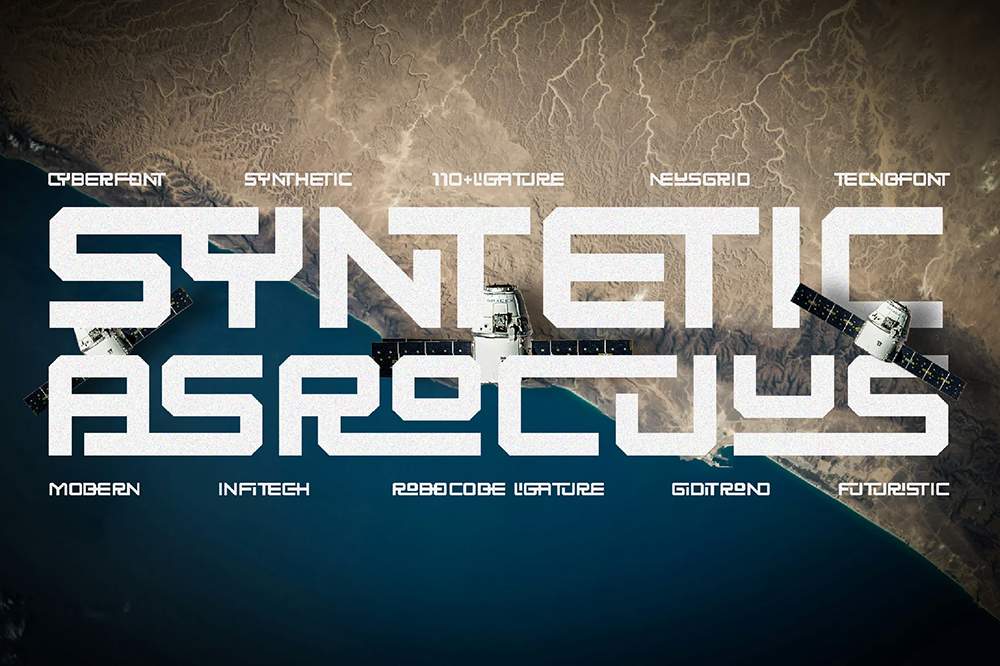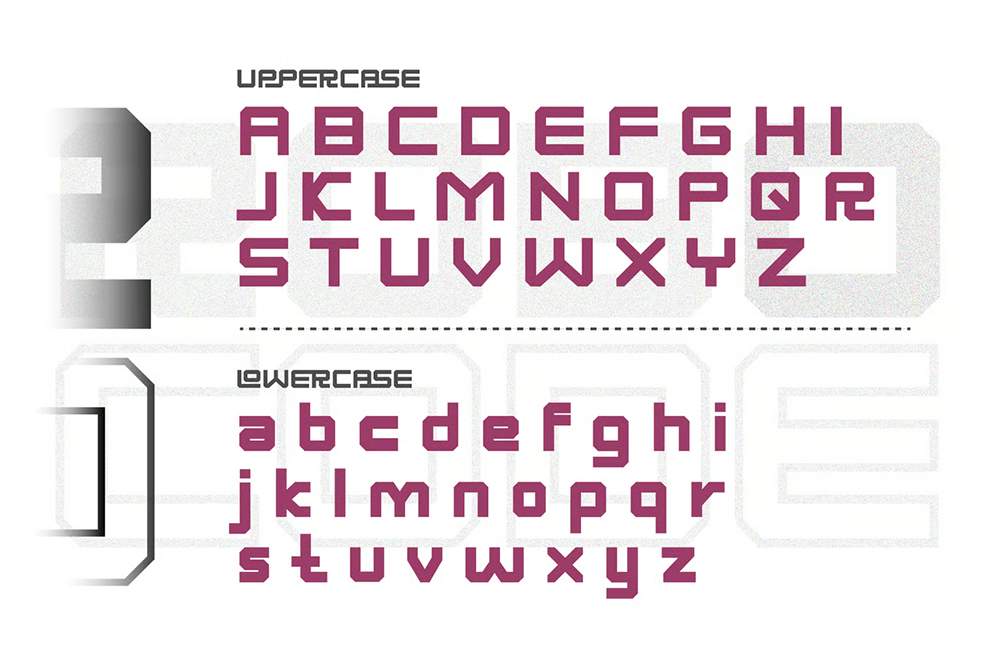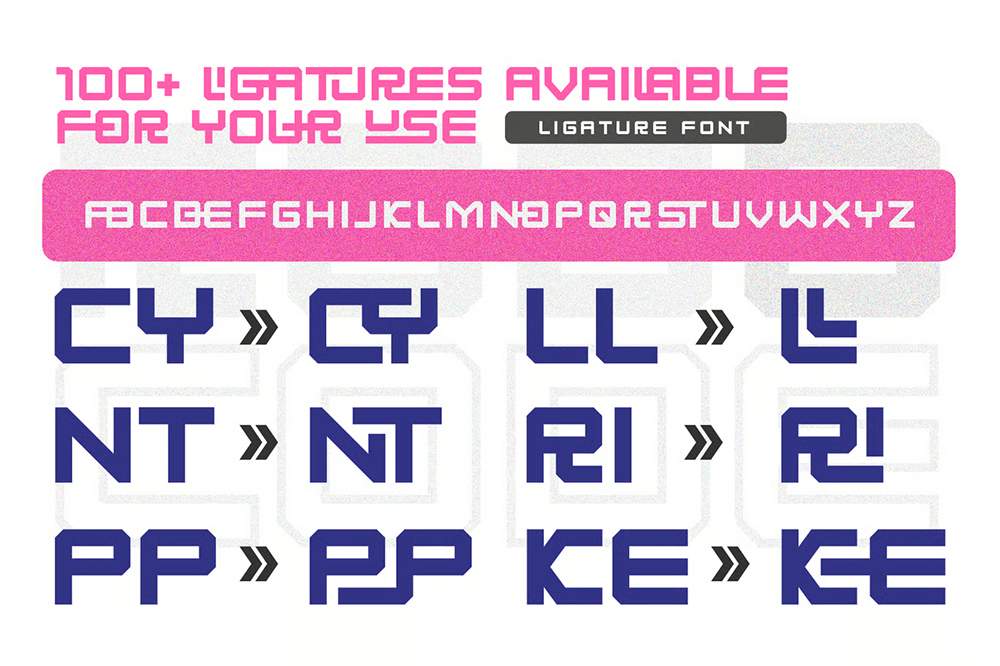
دانلود فونت انگلیسی Syntetic Asrocuus Font
فونت پرمیوم و انگلیسی Syntetic Asrocuus Font یک فونت لیگاتور پیشرفته است که با طراحی جسورانه، متقارن و آیندهنگرانه ساخته شده و برای پروژههایی با زیباییشناسی قوی فناوری ایدهآل است. اشکال هندسی ظریف آن، احساسی مدرن و نوآورانه ایجاد میکند و روح واقعی فناوری و آینده را به تصویر میکشد. Syntetic Asrocuus با طراحی دقیق، یک تجربه خواندن روان، پویا و چشمنواز را تضمین میکند. این فونت با پشتیبانی چندزبانه و سیریلیک، آماده ارتباط با مخاطبان جهانی است. چه برای برندهای مبتنی بر فناوری، طراحی UI/UX، رابطهای دیجیتال یا پروژههای بصری آیندهنگر، لبهای تیز و پیچیده ارائه میدهد که در هر کاربرد خلاقانهای برجسته است.
مزایای استفاده از فونت لاتین Syntetic Asrocuus چیست؟